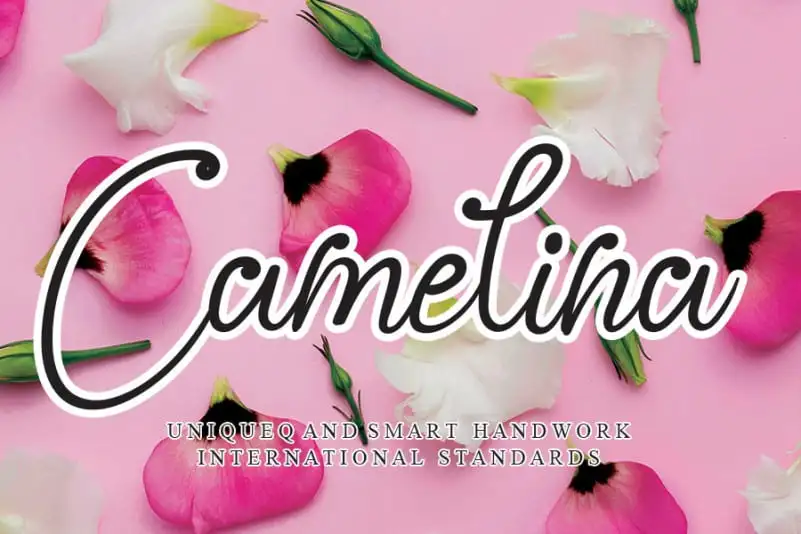
Camelina Handwritten Font – Download Grátis
A ‘Camelina Handwritten Font’ é uma deliciosa peça do design que oferece elegância e delicadeza num apelo natural à escrita a mão. Especialmente indicada para criar logomarcas e identidades visuais chamativas, bem como mensagens inspiradoras com citações, este fonte atinge o coração da criatividade. Cada letra é única, trazendo um toque especial que dá vida ao seu design. Perfecta tanto para aqueles trabalhos gráficos que procuram uma personalização sofisticada quanto para quem procura algo encantador e romântico. Sempre disponível em qualquer tamanho e grau de detalhe, a ‘Camelina Handwritten Font’ é definitivamente um recurso gráfico indispensável no seu kit de ferramentas.